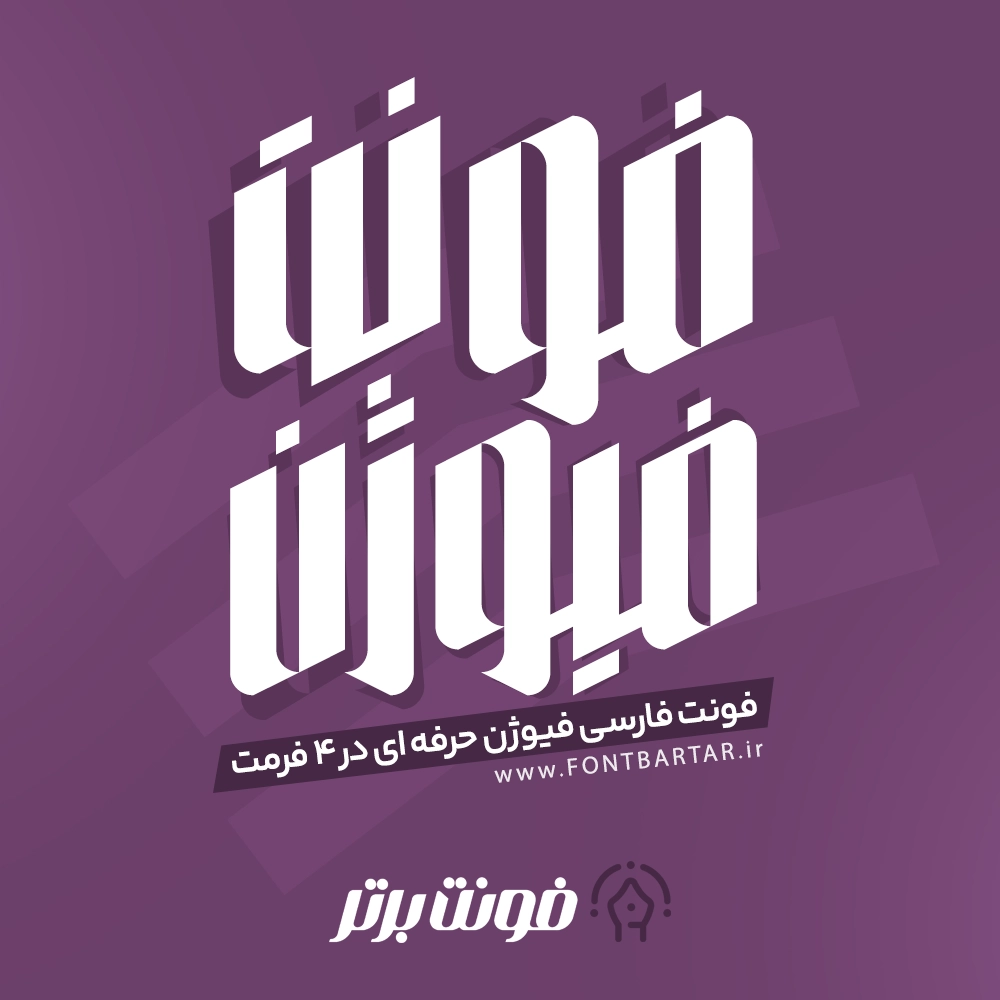
فونت جدید فیوژن
فونت لاکچری فیوژن
Fiyozhen Font
دانلود فونت فیوژن | فونت فارسی فیوژن حرفه‌ای در ۴ فرمت برای طراحی و تایپوگرافی
فونت لاکچری فیوژن یکی از جدیدترین و خاص‌ترین فونت‌های فارسی مدرن است که با ترکیب ساختار هندسی و خطوط ضخیم طراحی شده تا جلوه‌ای جسورانه و امروزی به نوشته‌های شما بدهد.
اگر در زمینه طراحی پوستر، لوگوتایپ، تبلیغات یا تایپوگرافی فعالیت دارید، فونت فارسی فیوژن می‌تواند انتخابی بی‌نظیر برای پروژه‌های حرفه‌ای شما باشد.
✨ ویژگی‌های فونت فارسی فیوژن
• 🔠 طراحی مدرن و هندسی با استایل بولد و خوانا
• 🧠 مناسب برای تایپوگرافی، طراحی لوگو، پوستر و بنر تبلیغاتی
• 🖋️ پشتیبانی از حروف فارسی و عربی کامل
🎯 کاربرد فونت فیوژن در طراحی
فونت فیوژن برای طراحی‌های مدرن و قدرتمند بسیار مناسب است. از جمله کاربردهای رایج آن:
• طراحی لوگوتایپ فارسی
• طراحی جلد کتاب و مجله
• فونت لاکچری برای اینشات
• پوسترهای تبلیغاتی و فرهنگی
• پست‌های اینستاگرامی و بنرهای دیجیتال
1. فونت فیوژن چیست؟
فونت فیوژن یک فونت فارسی مدرن و هندسی است که برای طراحی لوگو و تایپوگرافی‌های خاص ساخته شده است.